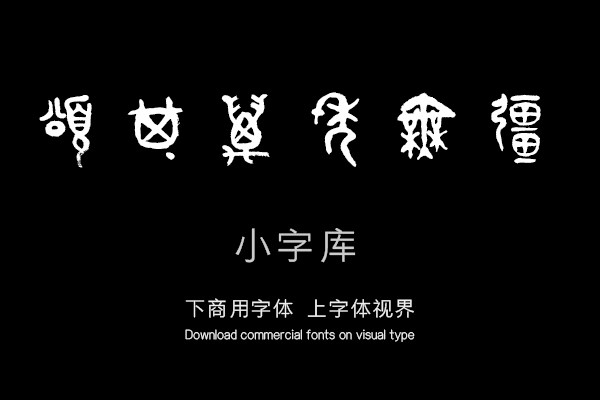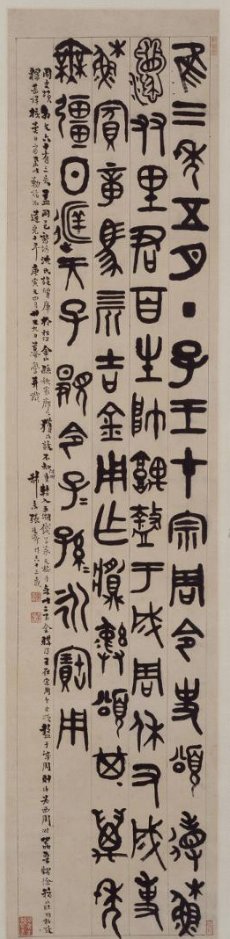
汉标张廷济篆书颂鼎铭
《汉标张廷济篆书颂鼎铭》是一款根据清代张廷济经典书法作品《临史颂鼎铭》,经过再次调整制作的小字库,该小字库共收录了该真迹作品中约76个字体。
唯三年五月丁巳,王在宗周,令史颂省稣,涸友里君百姓,帅堣盩于成周,休有成事。稣宾章、马三匹、吉金,用作䵼彝。颂其万年无疆。日扬天子觐命,子子孙孙永宝用。